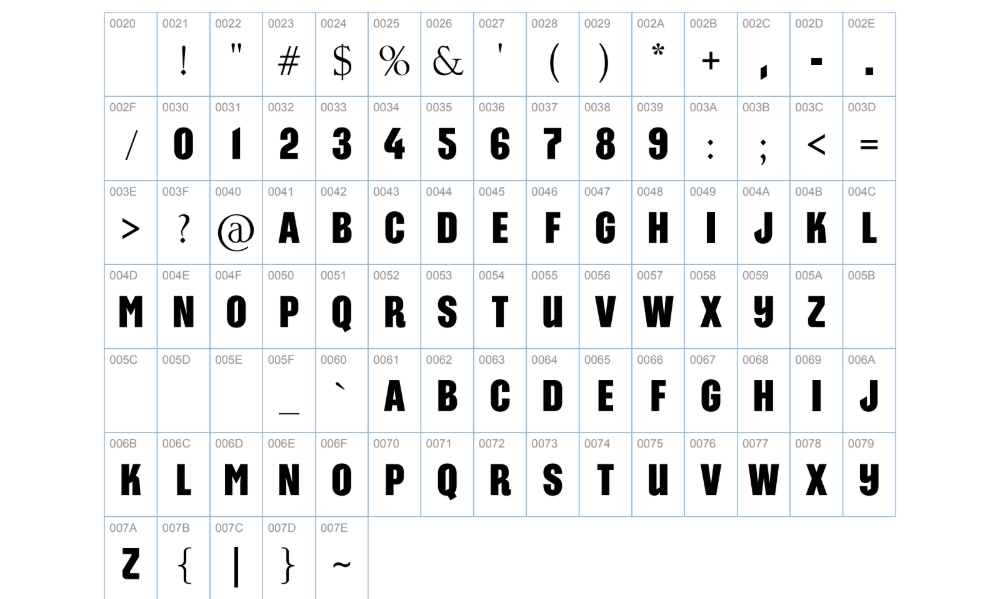
O futebol alemão é conhecido por sua identidade visual marcante, e o VfL Osnabrück mantém essa tradição viva na temporada 2025/2026. Vestindo as cores dos “Lila-Weiße” (Lilás e Branco), o clube traz para os gramados uma identidade renovada em parceria com a Capelli Sport.
- Conteúdo: Jogo completo de caracteres (caixa alta) e numeração oficial com detalhes internos.
Estilo Visual da Tipografia
A fonte do VfL Osnabrück para o ciclo 25/26 reflete a estética funcional e moderna típica do design alemão. Desenvolvida para harmonizar com os templates da Capelli Sport, a tipografia aposta em traços espessos e condensados, o que garante excelente leitura mesmo em movimento ou à distância.
O destaque visual fica por conta dos ângulos levemente cortados nas extremidades dos números, conferindo um ar tecnológico e agressivo, ideal para representar a competitividade das ligas alemãs. É uma fonte que funciona muito bem tanto em fundo roxo (Home) quanto nas variações monocromáticas (Away).